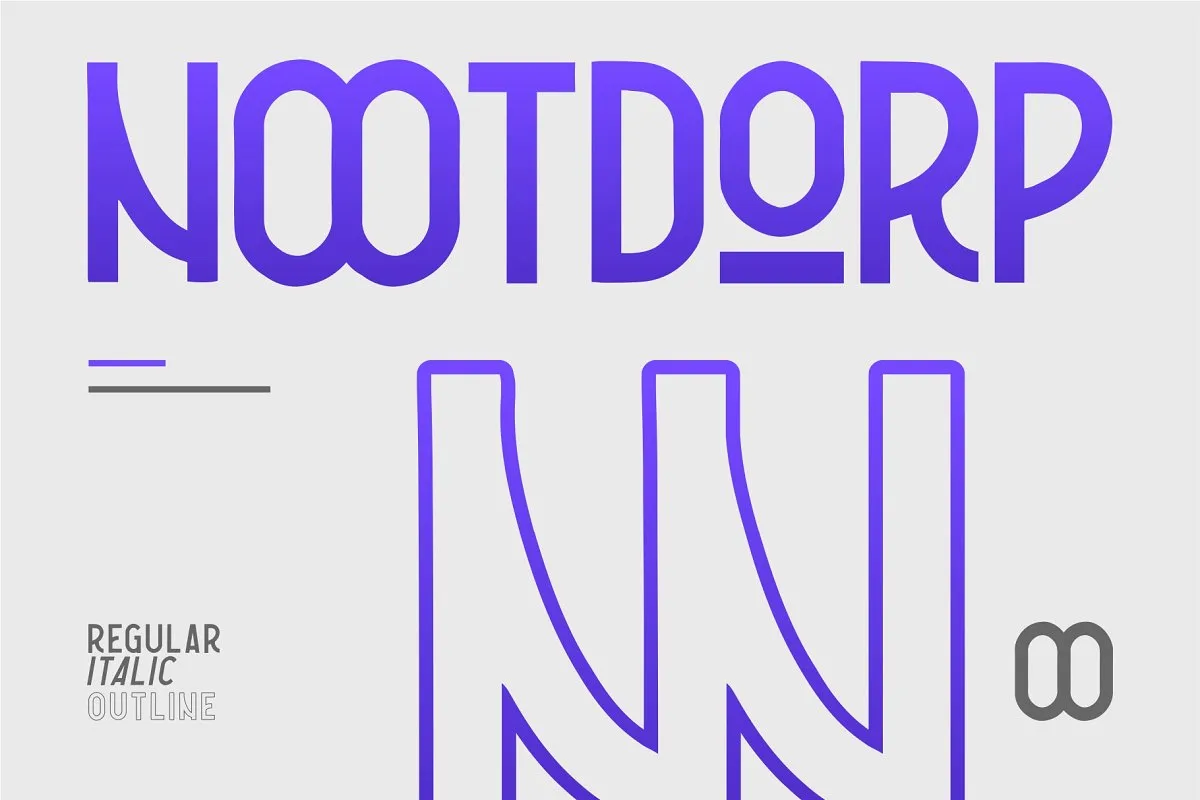
Nootdorp Typeface – Download Grátis
Esta é uma fonte tipo-display inspirada em anúncios clássicos e posters de filmes. Inspirada por tipografias modernas e poderosas, ela traz um forte tom retro industrial e esportivo, adequado para estilos vintage moderno. A Nootdorp Typeface foi criada para oferecer versatilidade em uma ampla gama de aplicações como marcas, rótulos, embalagens, logotipos, sites, cabeçalhos, headlines, revistas e muito mais. Incluímos três estilos nesta fonte: Regular, Italic e Outline. Perfeita para combinações com outras fuentes! Nootdorp é um projeto da 1001fonts, um designer brasileiro dedicado a criar novas e úteis fontes que se adaptam perfeitamente ao mundo digital atual. Nossos designs são ideais para designers gráficos, ilustradores e criativos de qualquer tipo, proporcionando uma variedade incrível e versátil em cada projeto.